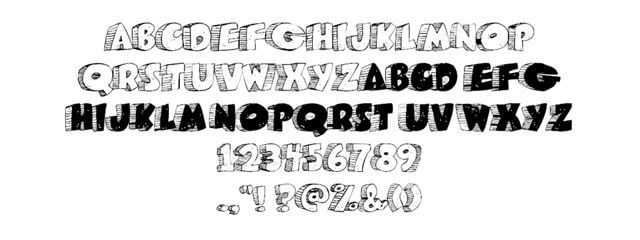
【無料】次のプロジェクトに使える3Dフォント25選
もしあなたが新しいフォントをいくつか探しているなら、ここに来て正解!ここでは、ダウンロードしてプロジェクトで使うのに最適な3Dフォントをいくつかまとめました。
見出し、タイトル、ポスター、グラフィック―目的が何であっても、いろいろな用途に役立つフォントを見つけられます。そしてなんといっても、これらのフォントはすべて無料です!
Green Piloww
Pointy Solid
Alpha Wood
Chunky
Walk Around the Block
Chocolate Drops Font
Block Tilt Font
Corn Fed Font
Cubicle
Coming Soon
Block Buster
Heavy Rotation
Action Jackson
Sans Poster Bold 3D
Stoney Billy
C Rial
Hot Dog
Caveman
Ricks American Cafe Font
Blog the Impaler
Pijamas
Augustus Beveled
Decade 3D Font
Blox
Pin Down X-BRK
Retro Sign